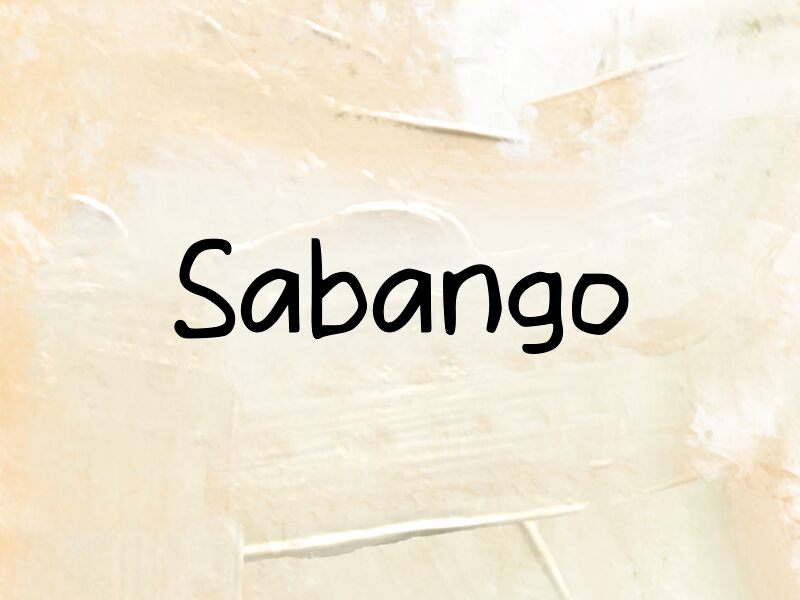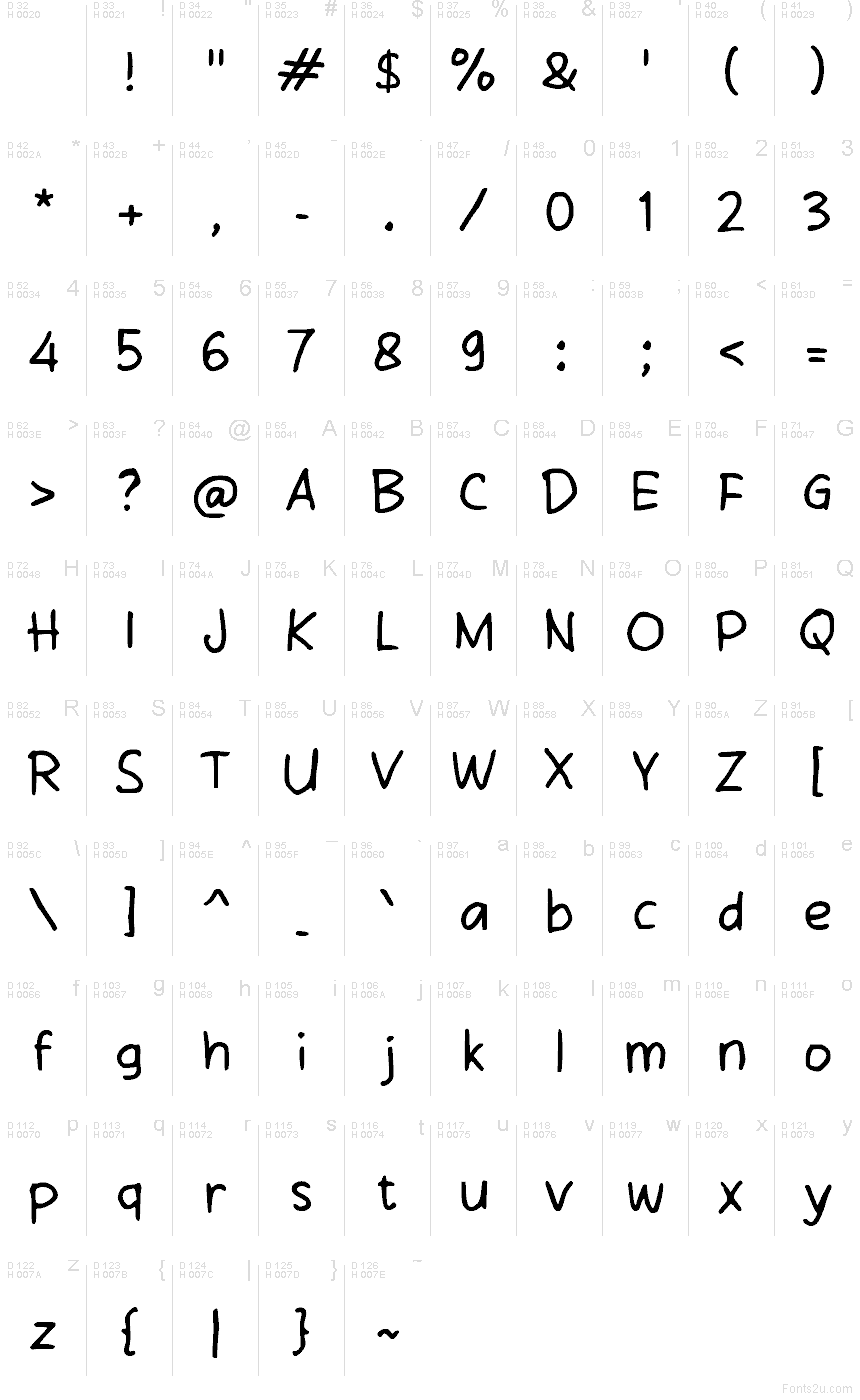
Sabango
Sabango 由 Wep 出品,是一款免费的手写字体。它拥有随意而灵动的节奏感,仿佛是用马克笔快速书写而成的。挺拔的竖笔与圆润的转折让字形充满了活力,呈现出一种随性自然的笔触,而非规整刻板的教学字体。
这使得 Sabango 成为咖啡馆菜单、贺卡、社交媒体引语、儿童产品包装及非正式海报标题的理想之选。其欢快起伏的韵律为短句增添了对话感,特别适合那些追求亲切感与一点点自发性的设计项目。